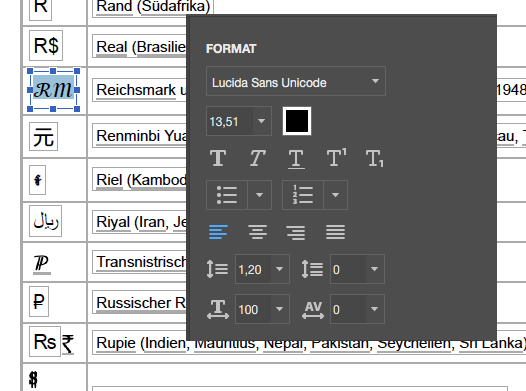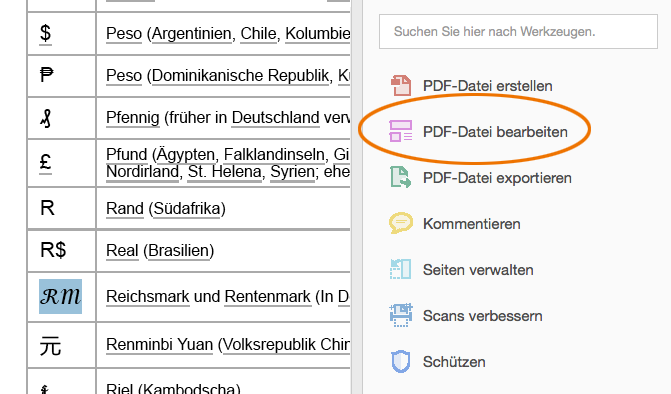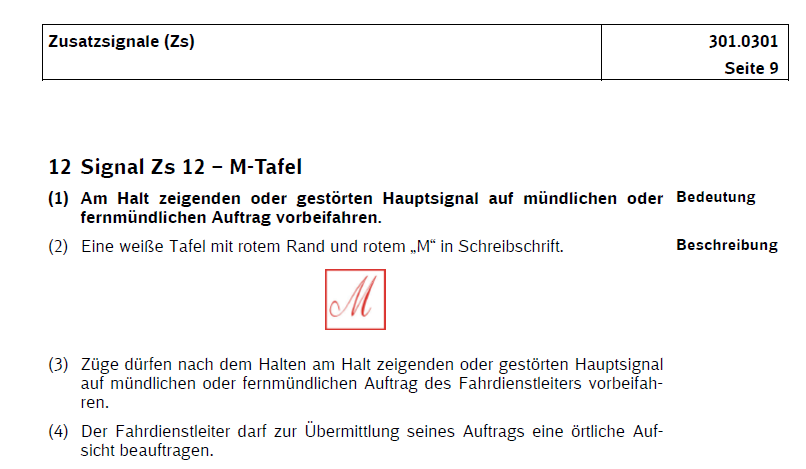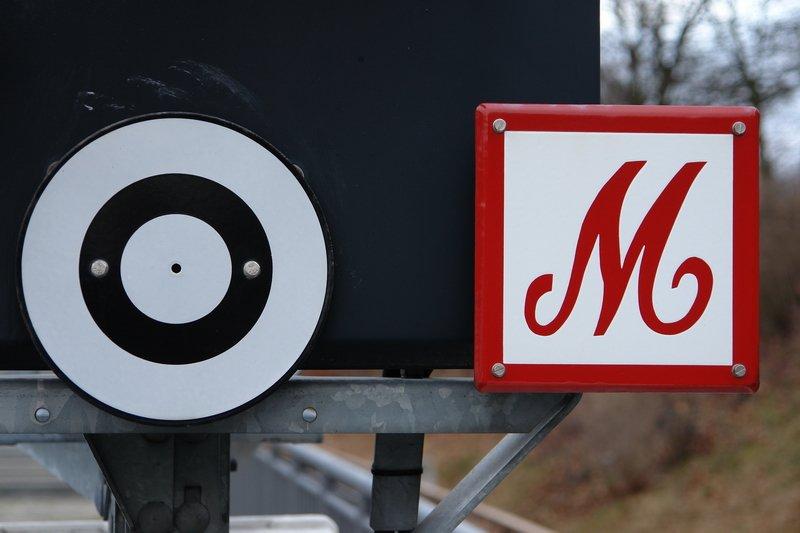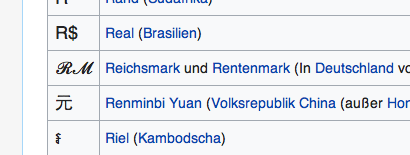
Währungssymbol Reichsmark /Mark
Hallo, auf der Wikipedia Seite bin ich auf Währungssymbole gestoßen die es aktiv nicht mehr gibt.
Welche Schriftart liegt hier zu Grunde?
Ich habe die Seite als PDF gespeichert und in Illustrator wieder geöffnet. Hier wurde nur Arial als fehlende Schrift angezeigt und die Währungssymbole werden auch nicht mehr angezeigt. bedeutet das, dass Arial diese Währungssymbole beinhaltet? Seltsam ist, das mir die Webseite das Symbol richtig anzeigt. Als WOFF wird hier nur die Schrift Lato angezeigt.
Die üblichen Wege habe ich alle durch, also in PDF nach der Schrift zu suchen. Als SVG sind die Symbole auch nicht eingebettet. Wenn ich die Schrift kopieren will und suche, wird in Google das Symbol noch richtig angezeigt wenn ich dann die Suche abschicke wird nach "RM" / "M" gesucht, allerdings nicht das was ich suche. Das Eichhörnchen  (https://www.fontsquirrel.com/matcherator) und verwandte Dienste hab ich auch schon bemüht.
Hatte die Deutsche Mark und Mark der DDR ein Währungssymbol?  Das war meine Ursprüngliche Suche.
Ok für Deutsche Mark hab ich was gefunden( s.u.  Quelle http://www.gr8ambitionz.com/2012/05/countries-and-currencies.html).
Interessant ist hier das die italienische Lira und das britische Pfund ein sehr ähnliches Symbol hatten.
Hat jemand noch eine Idee?
Nein, weder dir westdeutsche noch die Mark der DDR hatten ein Währungssymbol. es wurde in praktisch beliebiger Schrift nur M oder im Westen DM geschrieben.
Die Reichs / Rentenmark nach der Mega-Inflation wurde auch nur in Buchstaben geschrieben, nur die Ur--Reichsmark von 1871 hatte ein M in lateinischer Schreibschrift, also schon anders als dein Beispiel als Wärungssymbol. nämlich so ℳ
Ja toll lieber Peter, aber nun weiss ich noch nicht welche Schrift es ist ;-) ist der Eintrag also falsch? Siehe Bild
Wikipedia liefert lediglich den Unicode-Wert U+2133 für das Zeichen SCRIPT CAPITAL M an deinen Browser. Das nimmt der dann zum Anlass, das erste ℳ anzuzeigen, dass er in den lokal bei dir installierten Schriften findet, zuerst in der Reihenfolge, die im CSS-Fontstack der Wikipedia-Seite spezifiert wurde und dann nach den Default-Einstellungen deines Browsers und Betriebssystems.
Nach dem, was ich da kenne , ja. Dieses habe ich in alten Dokumenten nie gesehen, statt dessen hierfür entweder einfach RM in beliebiger Schrift oder als ℛℳ gesetzt.
ℳ = U+2133 (8499) (Letterlike Symbols Großbuchstabe Schreibschrift-M  für M-Matrix, M-Tafel der Bahn , Signal Zs12 Fahrt bei Halt nach mündlicher Aufforderung, sowie Reichsmark)
ℛ = U+211B (8475) (Letterlike Symbols Großbuchstabe Schreibschrift-R
Nein. Denn auch dort wird nur der korrekte Unicodewert benutzt. Dein Browser liefert dann dafür ein M mit mit oben liegenden Bögen aus. Wie das Währungssymbol in der vordigitalen Zeit üblicherweise aussah, wird ja auf der Wikipediaseite zur Reichsmark gezeigt:
Dass das Mark-Währungssymbol aus der Mode kam, ist übrigens nicht verwunderlich, geht es doch mit dem Niedergang der Fraktur als (quasi alleiniger) deutscher Alltagsschrift einher. Ein lateinisches, skriptiges M fällt innerhalb eines in Fraktur gesetzten Textes natürlich auf. Da sah man gleich: Aha, das ist ein Symbol. Aber innerhalb eines Antiquatextes ist das Mark-M eben praktisch nicht mehr von einem kursiven M zu unterscheiden. Da haben sich die Leute dann eben dran gewöhnt, Mark mit dem Buchstaben M abzukürzen. (Und für die Setzer war es so auch viel einfacher.)
Im pdf wurde die "Lucida Sans Unicode" verwendet.
wie hast du das so schnell herausgefunden Bertel?
OK UNI-Code hab ich jetzt verstanden, so wie es Peter zeigt. aber einen Rahmen bekomme ich nicht. Na egal ich hab die Lucida nachinstalliert, jetzt sehe ich es auch in Illustrator.
Ich sehe schon dass ich mich noch tiefer mit UNI-Code befassen muss.
pdf mit Acrobat öffnen, "RM" markieren und auf "PDF-Datei bearbeiten" klicken.